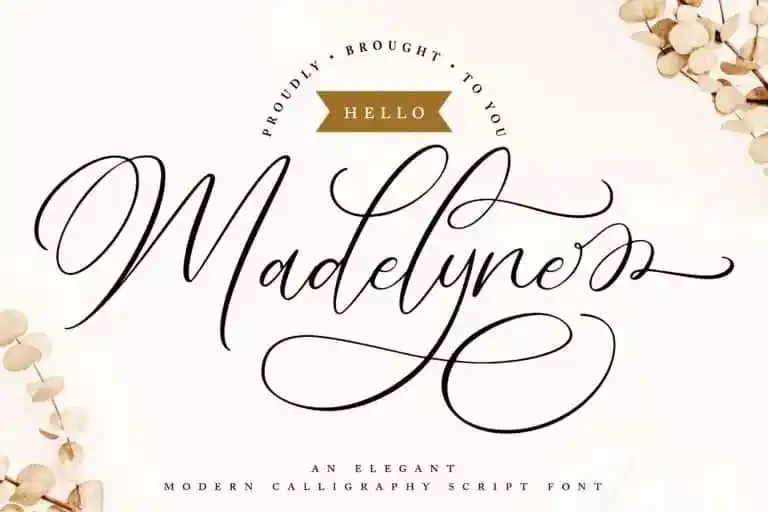
Hello Madelyne Calligraphy Font – Download Grátis
Introduzimos a fonte Hello Madelyne Calligraphy Font. Esta foi criada através do desenho à mão, apresentando formas modernas e únicas de calligrafia com um estilo natural. Ela é perfeitamente adequada para criar mensagens, convites de casamento ou design relacionado à beleza como logos, frases ou revistas. Desenvolvida pela Type Factory, esta fonte está localizada na categoria de scripts modernos e sua elegância se destaca especialmente em texturas que requerem uma graça especial. Ela é perfeita para estilos criativos, trazendo um ar de sofisticação ao seu trabalho sem parecer antiquada ou formal demais. Se você busca adicionar um toque especial a suas criações digitais, a Hello Madelyne Calligraphy Font está aqui para fornecer aquele pouco extra que torna tudo mais autêntico e único. Perfectly suited for modern and creative designers who want their work to stand out with the right amount of flair and personality.